表現・特徴で見つけるフォントBOOK モリサワ総合書体見本帳 2022-2023
モリサワは、1,500書体以上に及ぶMorisawa Fonts搭載書体を網羅した「表現・特徴で見つけるフォントBOOK モリサワ総合書体見本帳 2022-2023」を制作・刊行したこを発表した。
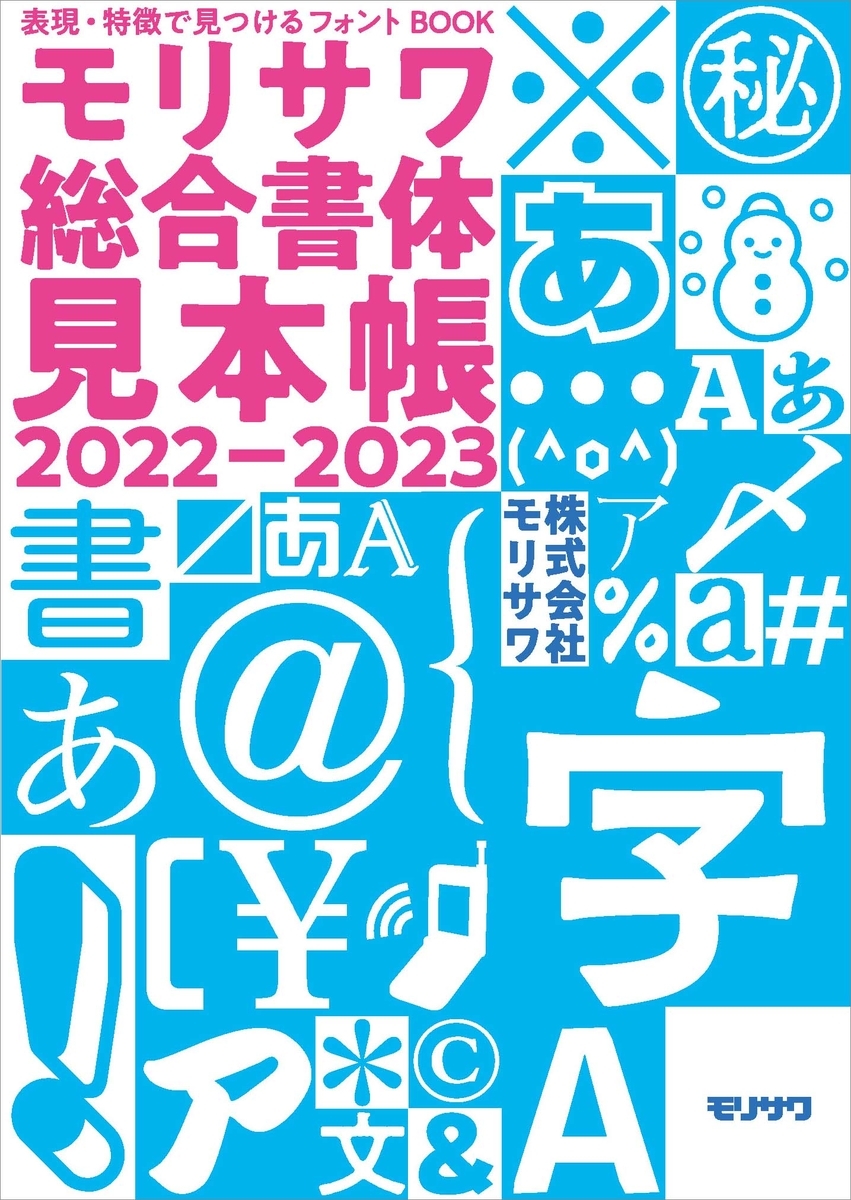
「表現・特徴で見つけるフォントBOOK モリサワ総合書体見本帳 2022-2023」は、従来の「明朝体」「デザイン書体」といった書体分類だけではなく、「つくりたい表現」や「特徴」といった親しみやすい独自のカテゴリで書体を見つけられる、使い手目線にこだわった見本帳となる。
「表現・特徴で見つけるフォントBOOK モリサワ総合書体見本帳 2022-2023」のコンセプト
「表現・特徴で見つけるフォントBOOK モリサワ総合書体見本帳 2022-2023」
実際にユーザーが書体を探すシーンを考慮し、より最適な書体にアクセスしやすく、各書体の個性を活かした使い分けができるように3つの検索方法を採用している。検索方法を複合的に使いながら目的の書体を探すことで、より制作物にマッチした書体が直感的に見つかる。
「表現・特徴で見つけるフォントBOOK モリサワ総合書体見本帳 2022-2023」特徴1.「つくりたい表現で探す」
「かわいい」、「楽しい」、「レトロ」、「物語性」など、表現したい作風やイメージにマッチする11種類のキーワードから書体を絞り込める。書体の使用シーンを彷彿とさせる組見本によって、ライブラリーの世界観を楽しみながら書体を見つけることができる。 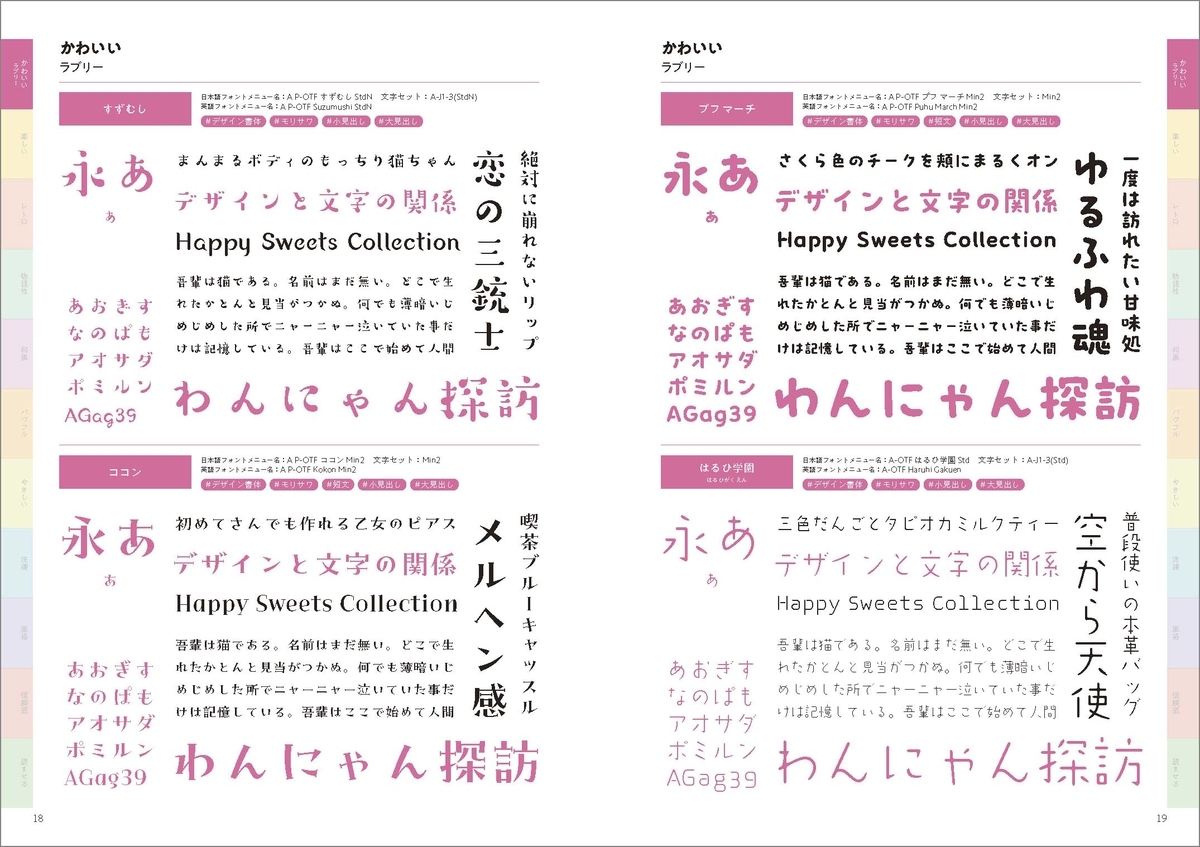
「表現・特徴で見つけるフォントBOOK モリサワ総合書体見本帳 2022-2023」特徴2.「特徴で探す」
「ペン字・手書き」、「コンデンス」、「教育用」など、形や仕様、用途といった具体的な特徴から関連する書体同士を比較できる。細分化された書体ジャンルによって、制作物に合った特徴を持つ書体を探すことができる。
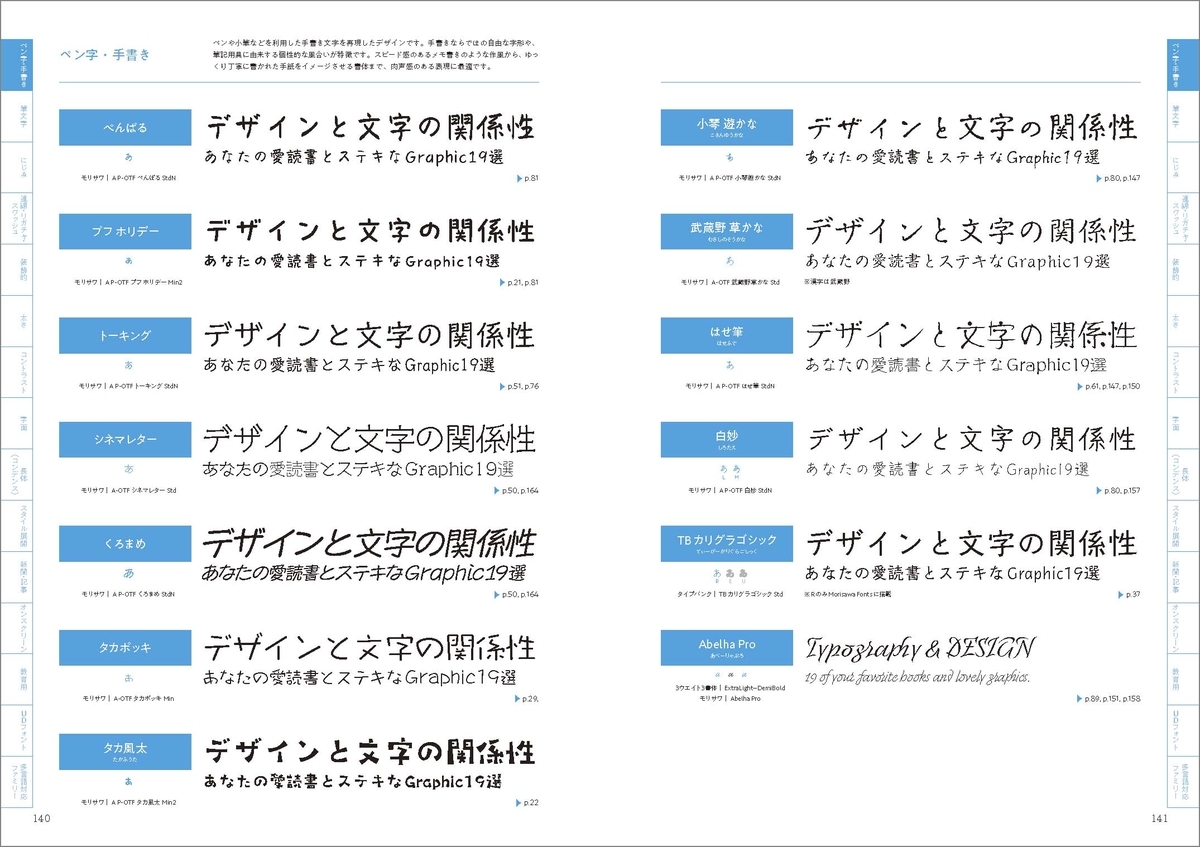
「表現・特徴で見つけるフォントBOOK モリサワ総合書体見本帳 2022-2023」特徴3.「全書体見本」
1,500書体を超えるMorisawa Fontsのライブラリーを、モリサワ、タイプバンク、字游工房、ヒラギノ、昭和書体の5つのブランドや多言語書体、および「明朝体」「ゴシック体」などの書体分類に基づいて網羅的に一覧できる。
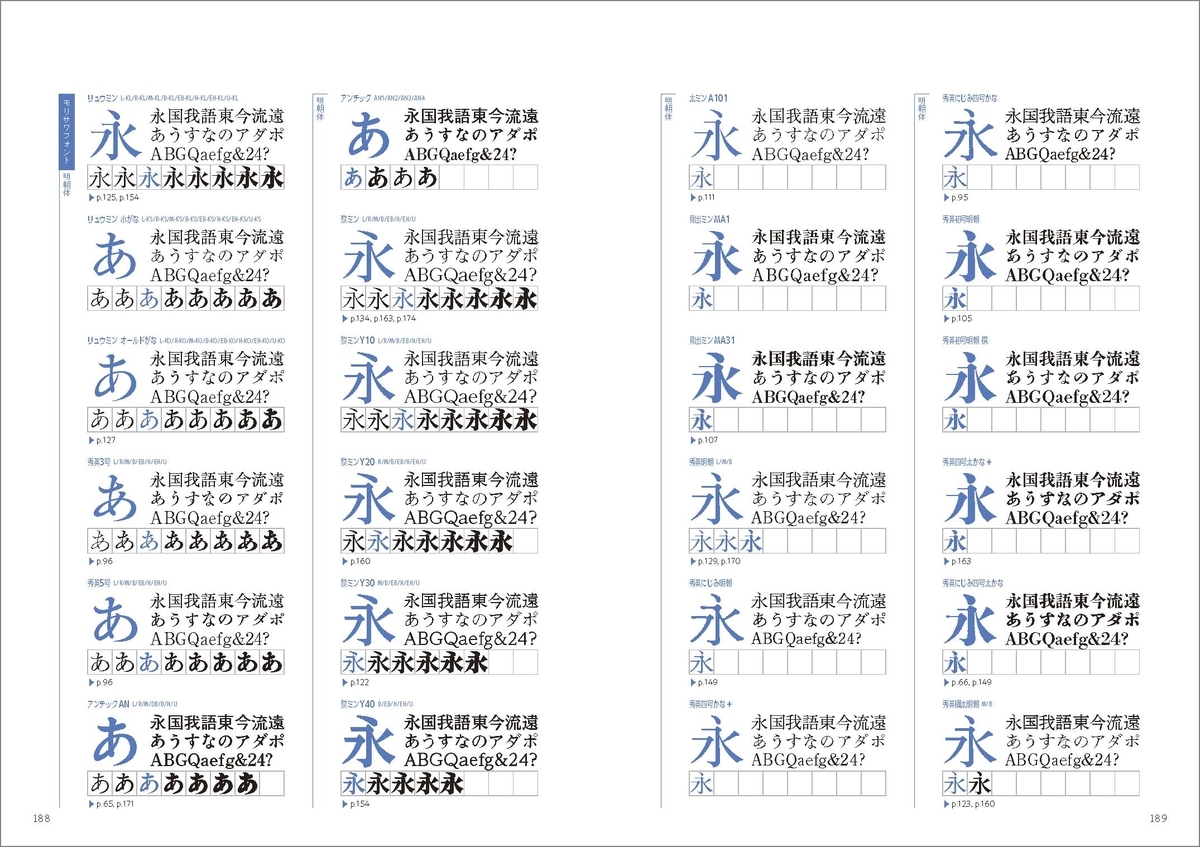
豪華な巻頭特集や役立つTipsを収録
特集企画は、ブックデザイナー松田行正氏による、モリサワフォントを使った6パターンの装丁作例を掲載。「文芸作品」、「ホラー&サスペンス」など、テーマに沿った書体の使い分けと組み方のアイデアが生み出す多様なデザインは必見。また、注目のUD書体の解説や、文字セットといったフォントに関する基本情報のほか、OpenType機能を使った字形の切り替え、カーニング設定など、フォントを使う上で役立つTips記事も掲載している。